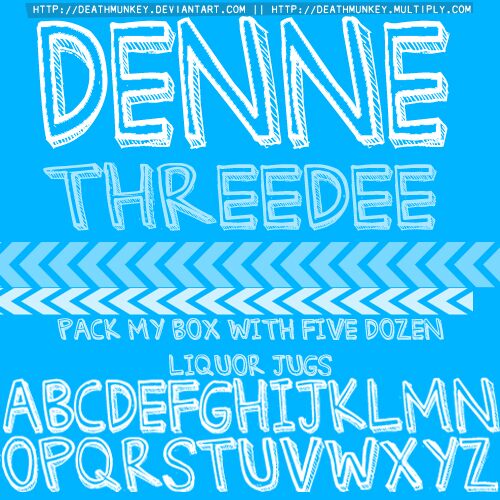
Denne Threedee, von Denise Bentulan, ist eine kostenlose, handgezeichnete 3D-Comic-Schrift mit fetten, umrandeten Versalien und versetzten Schatten. Lockere Konturen, ungleichmäßige Striche und kritzelige Schraffuren verleihen den Buchstaben den lebendigen Look von mit Markern gezeichneten Schildern, während die plastische Wirkung die Formen kräftig und verspielt erscheinen lässt.
Diese kostenlose Schrift eignet sich hervorragend für Comic-Cover, Kinderplakate, Spielegrafiken, Snack-Verpackungen, Event-Flyer und verspieltes Branding. Sie funktioniert besonders gut bei kurzen Überschriften und Titeln, wo die skizzierte Tiefe zur Geltung kommt, ohne das Design zu überladen.